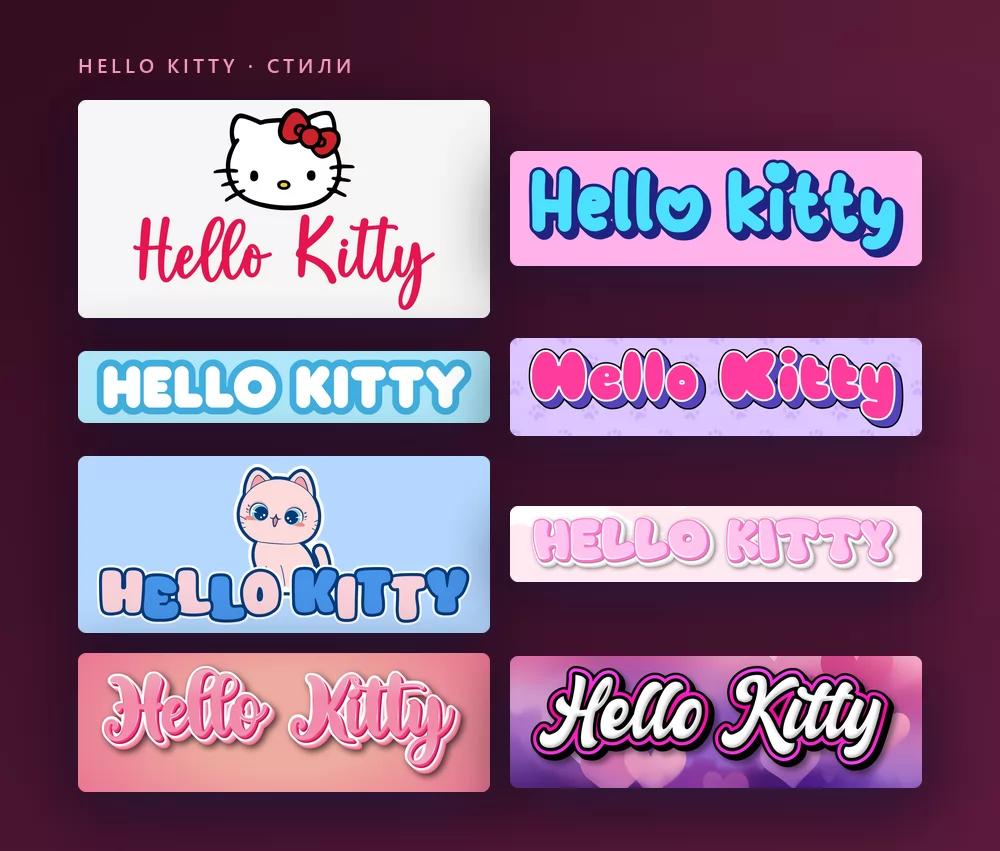
О шрифте Hello Kitty
Hello Kitty это японский персонаж, созданный в 1974 году для Sanrio дизайнером Юко Симидзу, а с 1980 года его рисует Юко Ямагути. Белая кошечка с красным бантом на левом ухе и без видимого рта впервые появилась на виниловом кошельке в 1975 году и стала одним из самых лицензируемых персонажей в мире, на игрушках, канцелярии, одежде и почти на всём остальном.
За годы логотип использовал несколько надписей, и ни одна из них не выпускалась как шрифт: это леттеринг на заказ, нарисованный для Sanrio. Поэтому «шрифт Hello Kitty» для разных людей значит разное, и поэтому сайты шрифтов перечисляют похожие варианты, а не один ответ. В каждом списке встречаются Janda Happy Day, Boldins, Odin Rounded, Jam Sessions, Hello Heartache и LMS Hello Kitty Hello.
Одно нужно знать до того, как что-то скачивать: самый скачиваемый шрифт «Hello Kitty», работа Woodcutter на DaFont с полутора миллионами скачиваний, это шрифт-дингбат. Каждая клавиша печатает маленький рисунок Китти, а не букву. Мило, но имя им не написать.
Как сделать текст в стиле Hello Kitty
Шаг 1. Введите имя
Откройте генератор и замените пример своим текстом: имя ребёнка, «С днём рождения», слово для обоев на телефон. Буквы перерисовываются прямо во время набора, под мордочкой Китти. Оставьте обычный регистр: стиль логотипа это рукописный шрифт, и слово прописными теряет соединения, из-за которых оно читается как написанное от руки.
Шаг 2. Выберите стиль
Классика это красная надпись под белой мордочкой на бледно-сером фоне. На вкладке «Стили» заливка, обводка и тень меняются отдельно, так что форму букв можно оставить, а цвета увести в другую сторону: мягкий розовый, пастельный голубой для праздника в стиле Cinnamoroll, белый на сердечках.
Шаг 3. Выберите формат
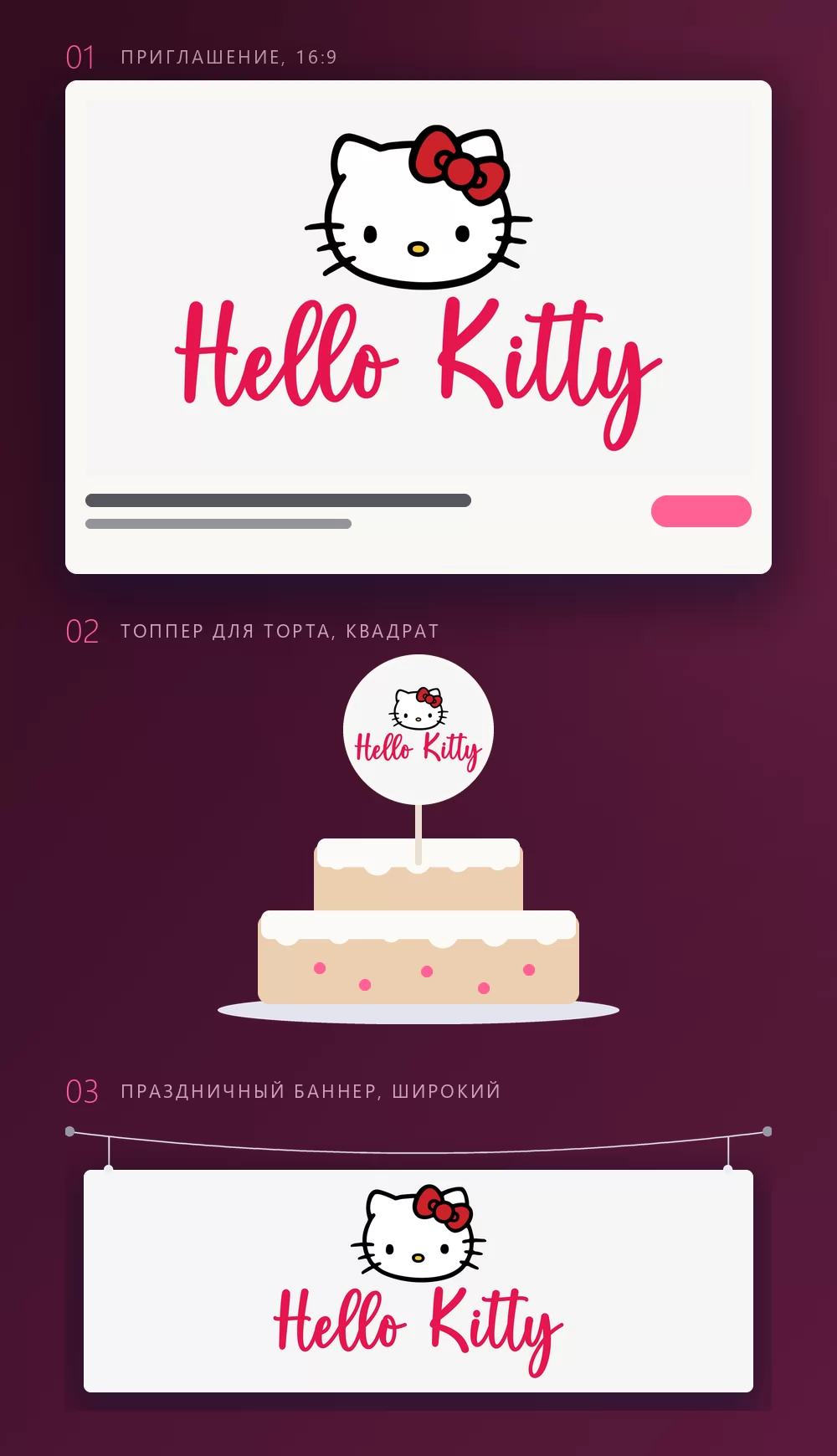
Задайте формат до экспорта, и потом ничего обрезать не придётся. 16:9 для приглашения, квадрат для топпера на торт или наклейки, широкая полоса для баннера через всю стену. Три макета выше показывают, во что превращаются эти форматы после печати.
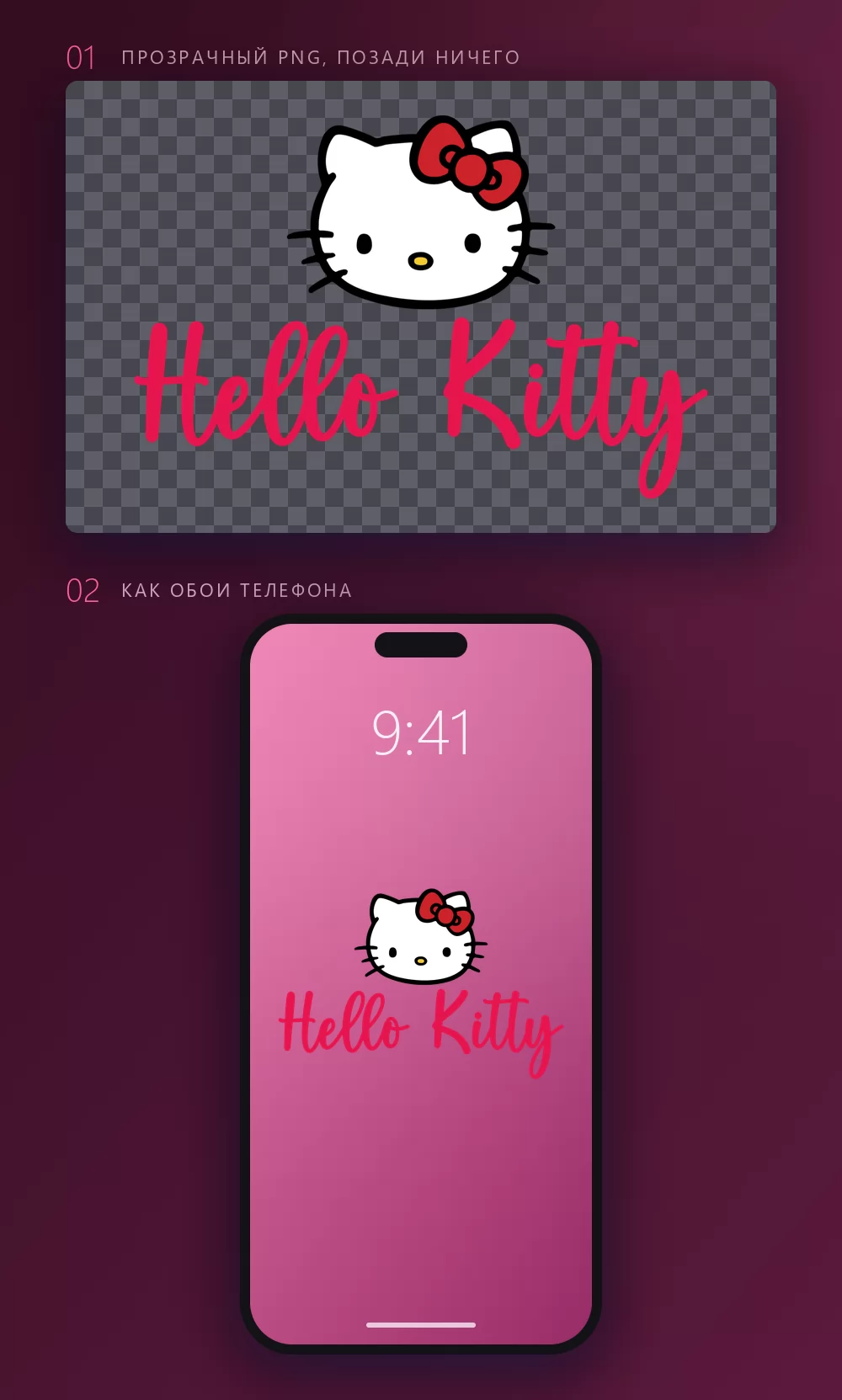
Длинные имена быстро заполняют ширину
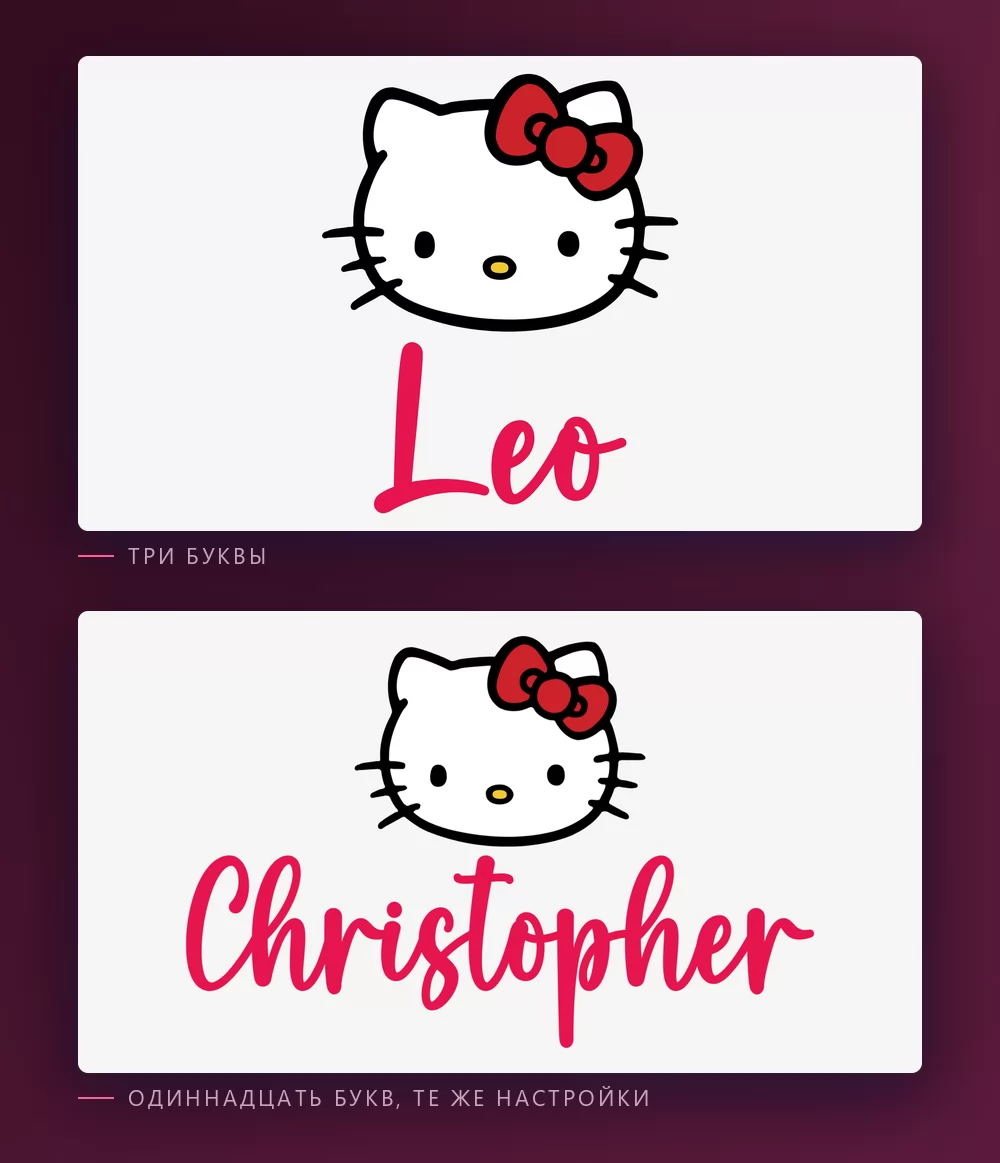
Чем больше букв, тем плотнее они сидят. Межбуквенный интервал это ползунок на вкладке «Текст»: чуть раздвиньте, и длинное имя перестанет выглядеть сжатым. На той же вкладке масштаб, межстрочный интервал, изгиб и поворот.
Стиль Hello Kitty или стиль кавай
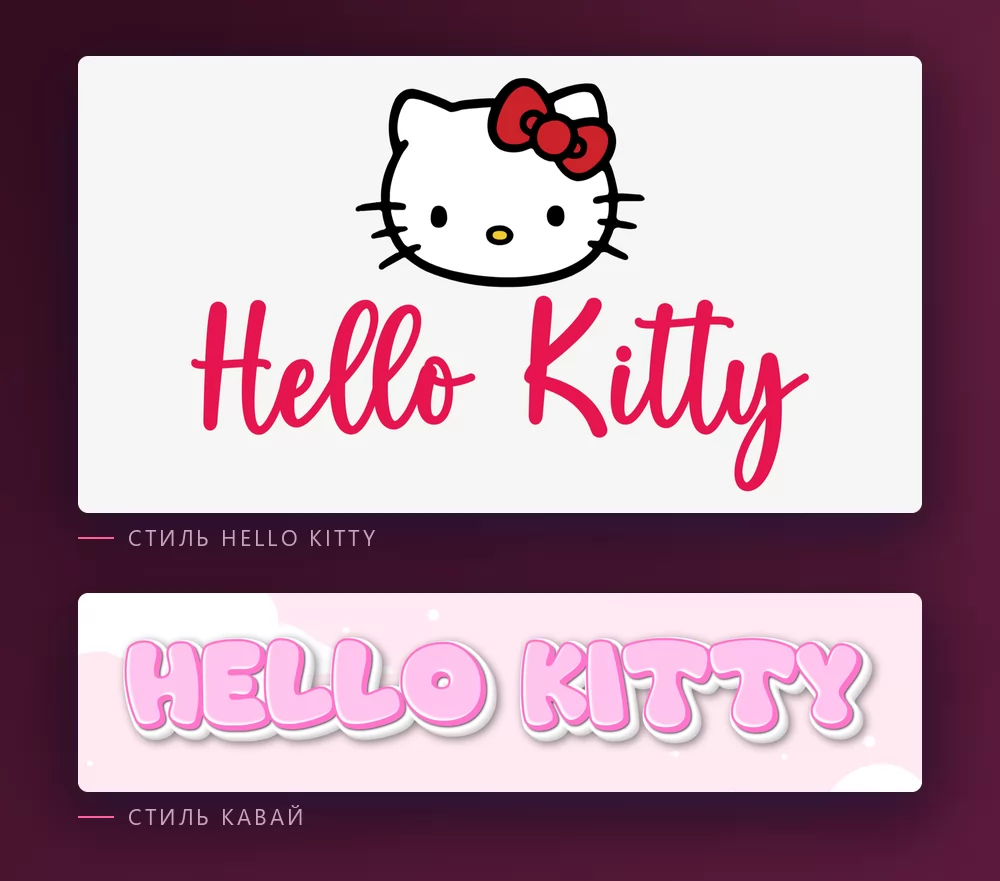
Стиль Hello Kitty это сам логотип: белая мордочка с красным бантом и имя красной рукописной надписью под ней. Именно это большинство представляет, и именно он нужен всему, что должно с первого взгляда говорить «Hello Kitty».
Стиль кавай это розовые пузырчатые буквы на пастельных облаках, без персонажа. В нём нет ничего от бренда Sanrio, и потому он лучше подходит для ежедневника, вывески магазина или обоев на телефон, которые просто должны быть милыми. В генераторе кавайного текста он есть как готовый стиль.
Какой шрифт, если вы хотите его установить
Сам логотип это не шрифт. Это леттеринг, нарисованный на заказ для Sanrio, поэтому любой файл с названием «шрифт Hello Kitty» является чьим-то воссозданием или просто похожим шрифтом.
Janda Happy Day от Кимберли Гесвейн большинство списков ставит первым: подпрыгивающая округлая рукописная надпись, которая читается как логотип. На DaFont она указана как бесплатная для личного использования, больше восьмисот тысяч скачиваний.
Odin Rounded это бесплатный шрифт с чистой лицензией: простой округлый гротеск, указанный на DaFont как полностью бесплатный, больше полумиллиона скачиваний. Он даёт мягкое округлое ощущение словесного знака без подпрыгивания.
Boldins это ещё один рукописный шрифт для личного использования из списков, а LMS Hello Kitty Hello, на FontSpace с 2001 года с более чем миллионом скачиваний, это freeware только для некоммерческого использования. Прочитайте readme, прежде чем любой из них попадёт на то, что вы продаёте.
Для работы с клиентами, где лицензия должна быть чистой, честные варианты это округлые шрифты с открытой лицензией на Google Fonts: Comfortaa, геометрический округлый шрифт, ближе всего к словесному знаку, и Fredoka, более подпрыгивающий, с полным набором начертаний. Ни один из них не шрифт Hello Kitty. Оба дают мягкий округлый вид с лицензией, которую никто не оспорит, и оба доступны в Canva.
Что с ним делают на самом деле
Генератор используют для того, на чём Hello Kitty всегда и жила: приглашения на день рождения и топперы на торт, наклейки для ежедневника или ноутбука, обои на телефон, бейджи с именами, праздничные баннеры и изредка вывеска магазина. Почти всё это лучше работает с прозрачным PNG, чем с установленным шрифтом, потому что вид это мордочка и красная надпись вместе, а файл шрифта даёт буквы и ничего больше.
Почему мой текст выглядит не так рядом с настоящим логотипом? Обычно дело в отсутствующей мордочке, а не в шрифте. Красная надпись сама по себе это просто красная надпись. С белой мордочкой и красным бантом над ней она читается как Hello Kitty даже в другом шрифте.